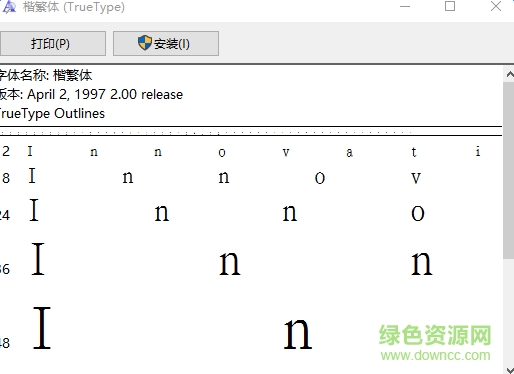
四通利方楷繁體字體是四通利方字庫(kù)中很不錯(cuò)的一款繁體字體,這款字體寫(xiě)出來(lái)的字是很好看的,不像很多字體那樣呆板沒(méi)有活力,用于書(shū)畫(huà)題字題詞還是很好看的,歡迎大家來(lái)綠色資源網(wǎng)下載。
四通利方楷繁體是一款繁體字體,繁體字體一般都是很有個(gè)性、很有特色的,雖然會(huì)比較難認(rèn),但是很好看哦,喜歡的朋友可以來(lái)綠色資源網(wǎng)下載。